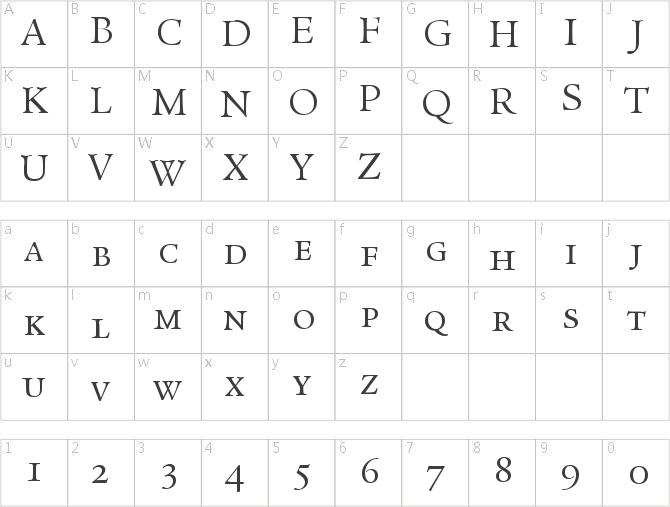
Legacy-Serif-SC-ITC-TT-Book 詳情頁(yè)
Legacy-Serif-SC-ITC-TT-Book字體字庫(kù)是一款讓人賞心悅目、百看不厭的英文字體,適合各類廣告和產(chǎn)品包裝設(shè)計(jì)應(yīng)用,字體大小0.08MB,格式為ttf字體,上傳用戶是我,Dirac,作者/版權(quán)方為未知